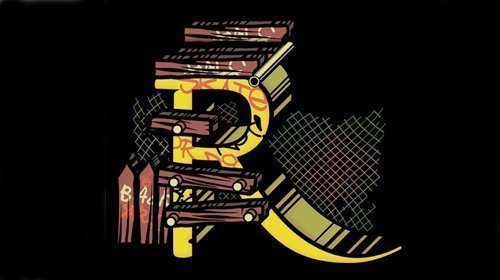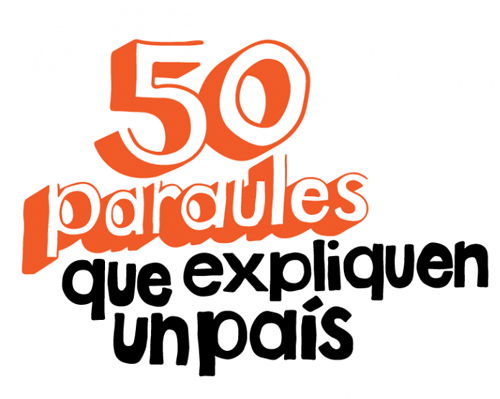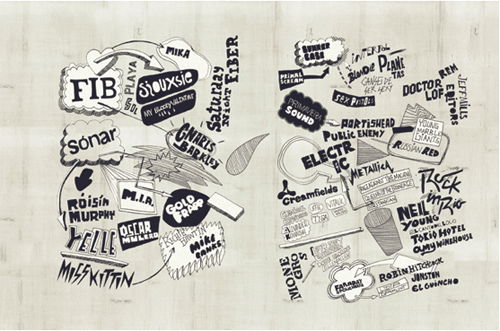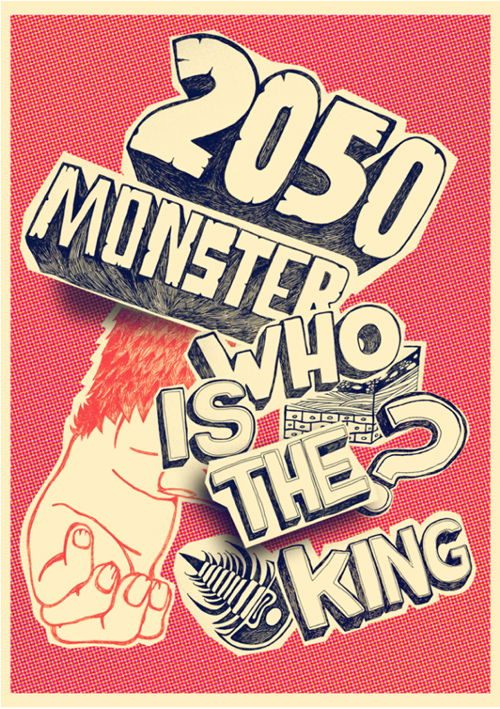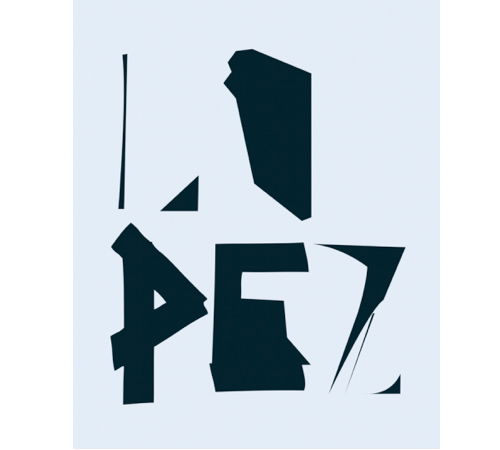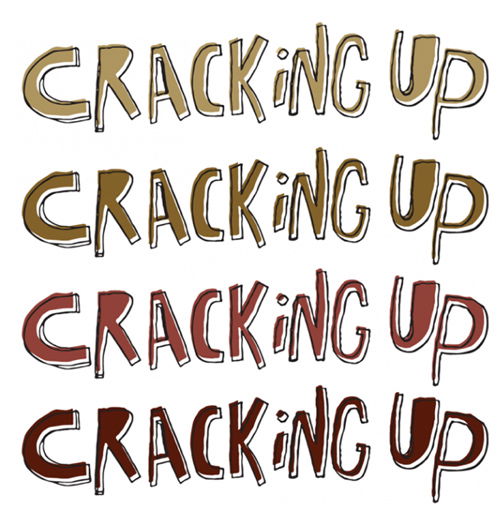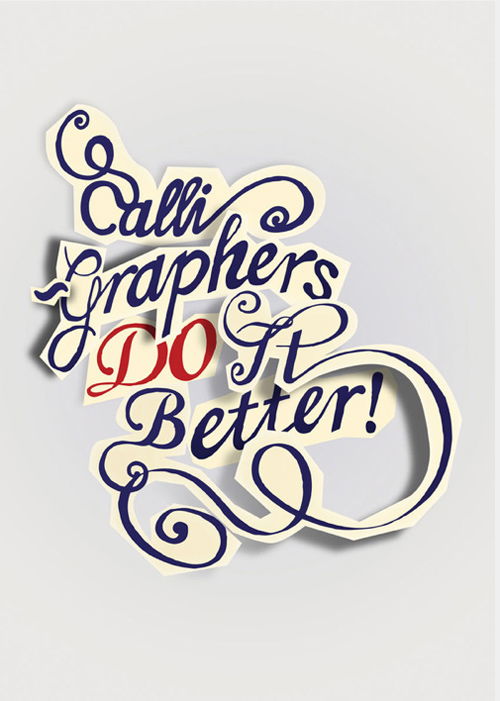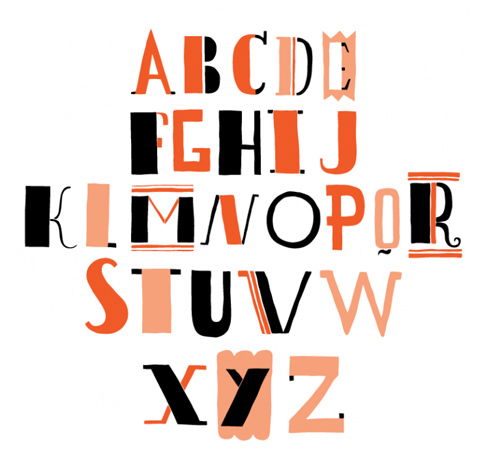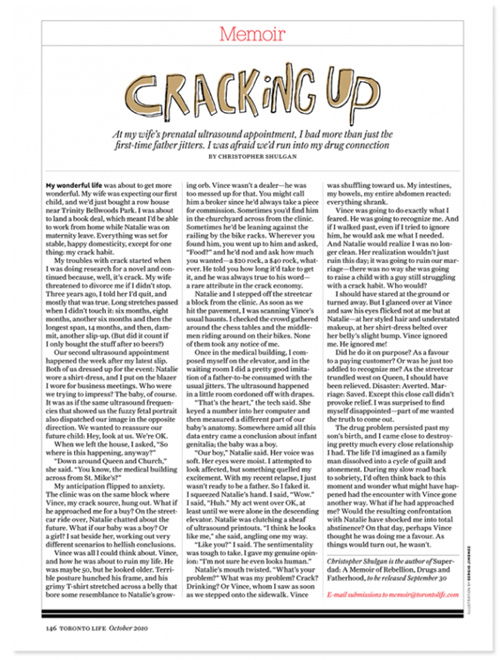
Subcoolture: Entre la caligrafía y la tipografía
Sergio Jiménez es, básicamente, “ilustrador”. No es tipógrafo, advierte. Aunque la letra dibujada le despierta un interés especial (“lo que fuera se denomina lettering y aquí de momento no tiene palabra que lo defina, algo entre la rotulación, la tipografía y la caligrafía”, matiza).
Cuenta que su trabajo “está a camino entre la caligrafía y la tipografía”. “Normalmente dibujo y desarrollo alfabetos o conjuntos de letras para proyectos concretos (titulares de revistas, periódicos, portadas de libros, mensajes publicitarios, etc…)”, explica el fundador del estudio Subcoolture. “Gran parte de los trabajos vienen inspirados por un tratamiento ‘amateur’ de la tipografía, es decir, se basan en imaginarios que tienen que ver con una gráfica de aficionado al diseño, caligrafía torpe, pintadas de la calle…”.
Estos son algunos de esos trabajos explicados por él mismo.
«Public es un proyecto de lettering para el periódico Público en Cataluña. La edición especial catalana (en el día de Sant Jordi) incluyó todos los titulares dibujados a mano y un alfabeto exclusivo para nombrar las secciones».
«Festivales de verano es una ilustración que hice para la revista Vanidad en relación a un artículo sobre los festivales de música veraniegos. Está realizada como una especie de mapa ‘mental’ donde uno se organizaba los conciertos a los que iba a ir. El tratamiento de las letras imita a la escritura sobre cintas de cassette».
«Poster Life in 2050 es un póster realizado para la exposición Life in 2050 organizada en Londres por This is Transmission con motivo del festival de cine de ciencia ficción. Está inspirado en los rótulos de películas Sci-Fi de los años 50-60″.
«LOPEZ. Lettering y tipografía realizado para el catálogo del artista Juan López, premio ABC de ARCO 2010. Las letras están tratadas como el trabajo del artista que suele intervenir sobre vinilo en la pared. El catálogo incluye un alfabeto programado en Fontlab para crear titulares».
«Toronto Life es un buen ejemplo de lettering de una revista canadiense que suele encargarme titulares para artículos específicos. Normalmente el titular se ilustra en función del contenido del texto».
«Petrantoni Font es un gustazo de proyecto de esos en los que trabajas para alguien a quien admiras. Conocí a Lorenzo en una charla que impartimos juntos en Bilbao y de ahí surgió la colaboración. Él seleccionó y recortó un buen puñado de letras y yo me encargué de realizar la versión digital y la programación en Fontlab, para convertirlo todo en tipografía».
“Rousselot es un póster homenaje que hice para la exposición del IV Congreso de Tipografía de Valencia. Ricardo Rousselot es uno de los grandes calígrafos y mi propuesta juega con la torpeza de no saber escribir bien. Un tributo a partir de la ‘mala escritura”.